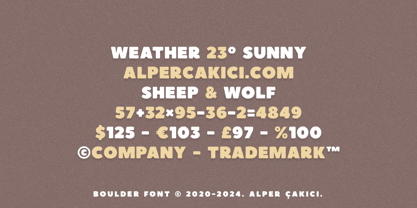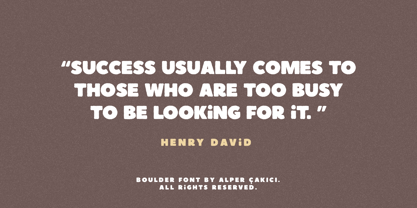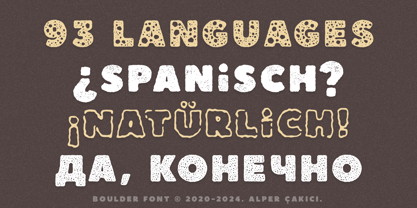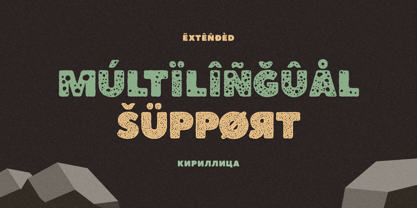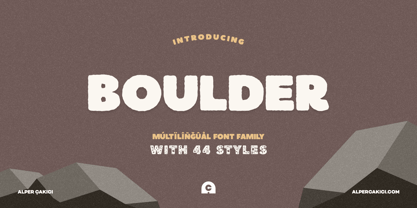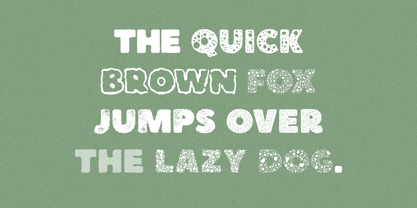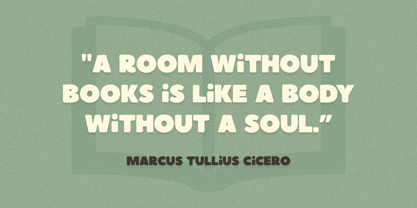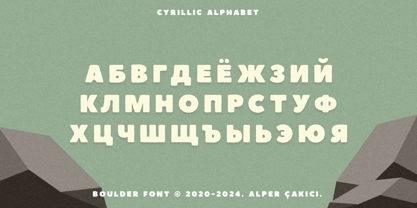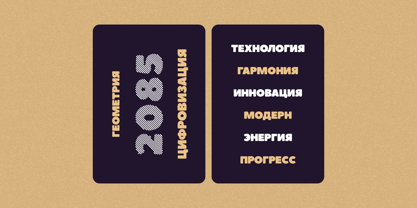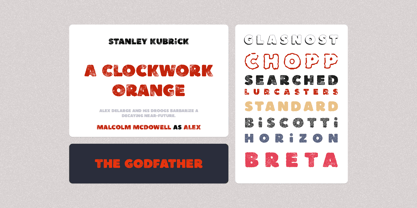
Boulder
por AlperCakici
La familia tipográfica Boulder fue diseñada por Alper Çakıcı y publicada por AlperCakici. Boulder contiene 44 estilos y opciones de paquete familiar.
Boulder is a modern, versatile font with excellent kerning, making it ideal for both digital and print use. It features full support for the Cyrillic language, allowing for seamless multilingual communication. Boulder's unique design combines classic proportions with a contemporary feel, making it stand out from other same categories fonts.